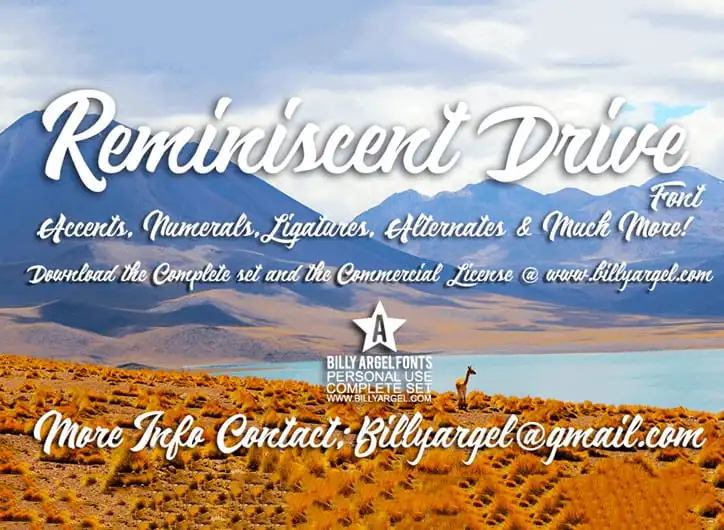
Reminiscent Drive Font – Download Grátis
A fonte “Reminiscent Drive” é uma proposta elegante e sofisticada para artistas e designers que desejam adicionar um toque único a seus projetos. Inspirada nas linhas curvas fluidas do calligrafia, essa fonte exala elegância e modernidade. Ela foi criada pelo talentoso designer Hamilton para quem busca uma abordagem sofisticada em seus trabalhos. Através da “Reminiscent Drive”, você pode capturar o espírito de uma viagem nostálgica através das letras, proporcionando um toque único e inovador a qualquer projeto. Esta fonte é ideal para criações que exigem um equilíbrio perfeito entre elegância e originalidade. Não se limite à sua imaginação – combine essa fonte com outros recursos gráficos para criar designs realmente únicos. Sua disponibilidade inclui versões gratuitas de uso pessoal, bem como opções completas e licenças comerciais disponíveis no website de Hamilton: www.billyargel.com. Aqui você encontrará mais detalhes sobre a fonte, além da oportunidade de se inscrever para receber novidades do designer. Acesse também o Facebook oficial de Hamilton para acompanhar as atualizações e lançamentos.